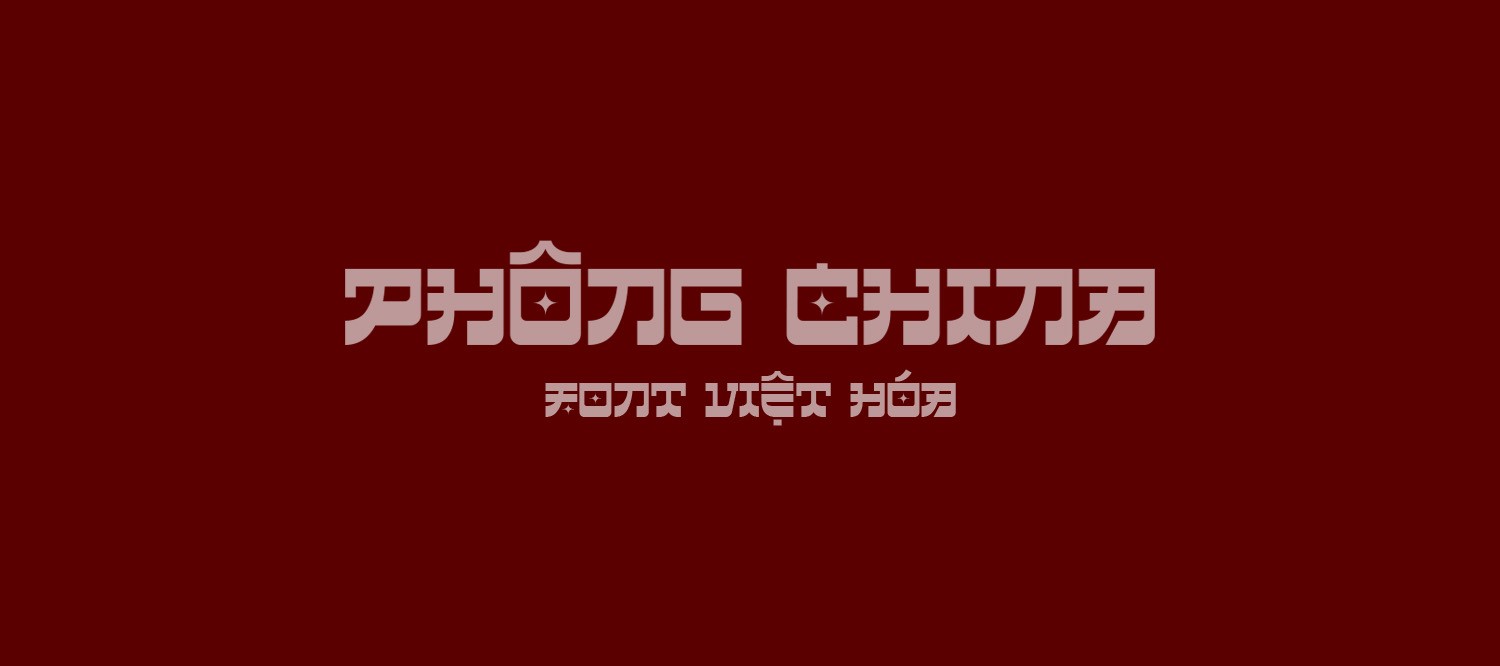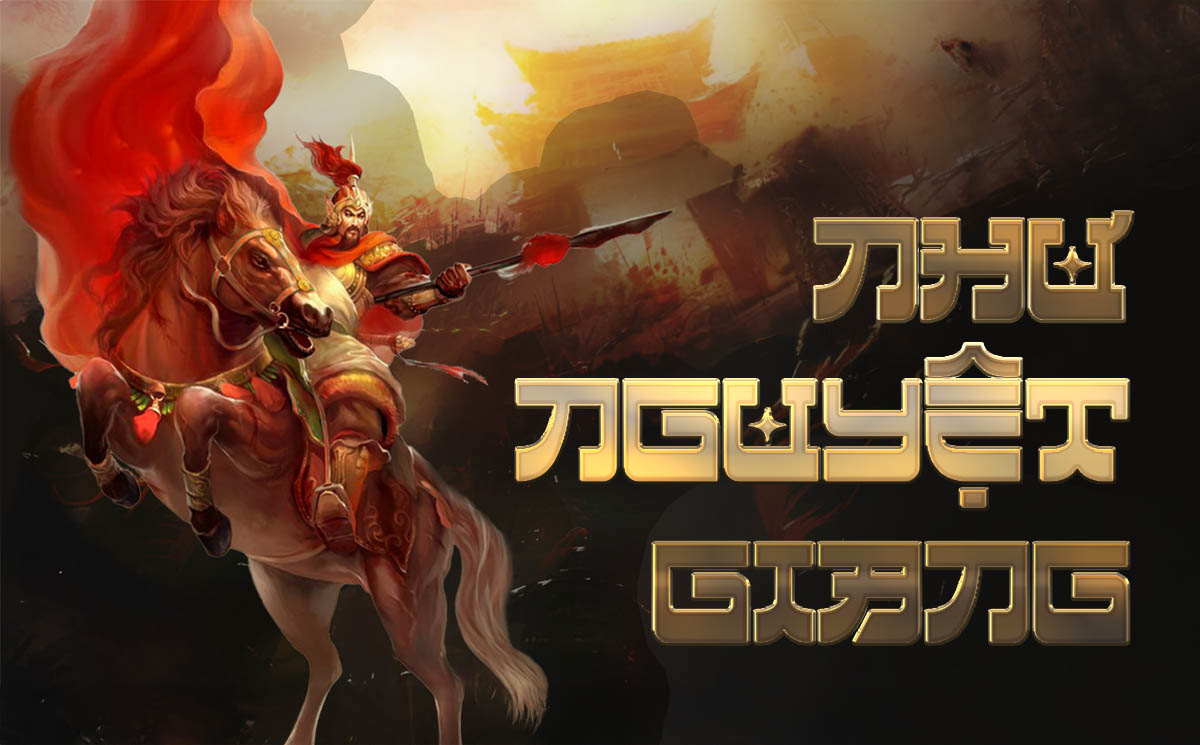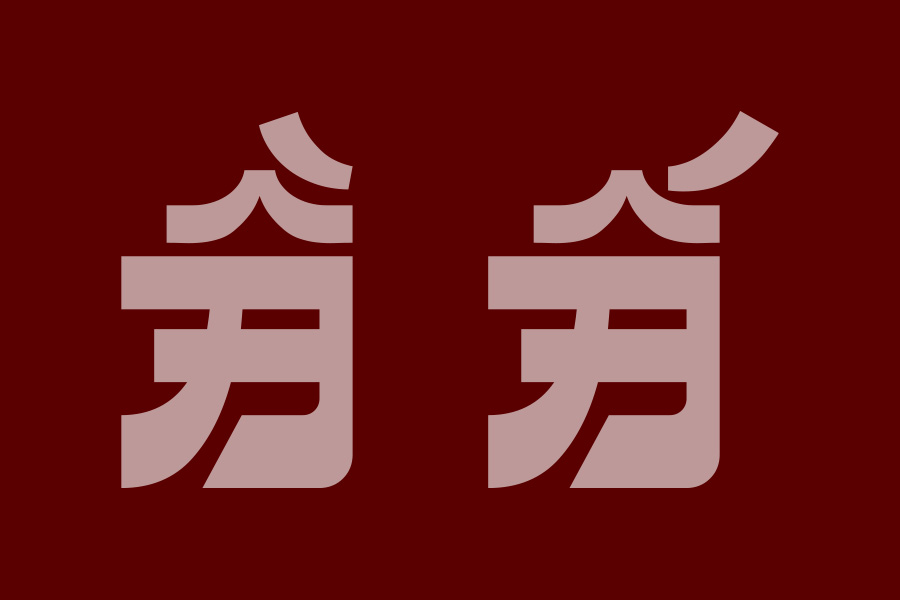
Font chữ TH China 1 là một sự lựa chọn tuyệt vời dành cho những ai yêu thích sự kết hợp giữa font chữ lịch sử và phong cách hiện đại. Lấy cảm hứng từ hình dáng chữ Hán, font chữ này sở hữu thiết kế mạnh mẽ, vuông vắn và đậm chất tương lai. Với kiểu dáng độc đáo, TH China 1 đặc biệt phù hợp cho các dự án liên quan đến văn hóa Trung Quốc, như lễ hội truyền thống, du lịch hay bất kỳ sự kiện nào mang đậm dấu ấn Á Đông.
Điểm nổi bật của font chữ TH China 1 nằm ở phong cách thiết kế đậm chất font chữ xưa, gợi nhớ đến nét cổ kính của văn hóa Trung Hoa, nhưng vẫn có sự tinh chỉnh để phù hợp với thị hiếu hiện đại.
Đặc biệt, font chữ này đã được nhóm thiết kế S99.vn Việt hóa hoàn toàn để hỗ trợ đầy đủ các dấu trong tiếng Việt, bao gồm các chữ Ư, Ơ, Ê, Ă cùng dấu sắc, huyền, hỏi, ngã… Nhờ đó, TH China 1 không chỉ phù hợp với các dự án tiếng Trung mà còn trở thành công cụ đắc lực cho người dùng Việt Nam trong việc thiết kế những sản phẩm mang tính truyền thống.
TH China 1 không chỉ là một font chữ, mà còn là công cụ tái hiện tinh thần văn hóa và lịch sử. Với phong cách thiết kế lấy cảm hứng từ font chữ lịch sử, font này thích hợp để sử dụng trong các dự án:
Thiết kế chủ đề lễ hội: Đặc biệt phù hợp cho các dịp lễ như Tết Nguyên Đán hay các sự kiện văn hóa Á Đông.
Du lịch Trung Quốc: Các ấn phẩm quảng bá địa điểm, ẩm thực hoặc nét đẹp văn hóa Trung Hoa đều có thể sử dụng TH China 1 để tăng tính thẩm mỹ.
Dự án lịch sử: Làm nổi bật các giá trị truyền thống trong thiết kế sách, biểu ngữ hoặc ấn phẩm giáo dục.
Font chữ TH China 1 - font chữ Việt hóa bởi đội ngũ S99.vn mang đến sự giao thoa độc đáo giữa truyền thống và hiện đại, đáp ứng mọi nhu cầu thiết kế mang phong cách lịch sử và cổ điển. Với sự hỗ trợ đầy đủ các ký tự và dấu tiếng Việt, font chữ này không chỉ làm sống dậy tinh thần Á Đông mà còn mở ra cơ hội sáng tạo cho các nhà thiết kế Việt Nam.